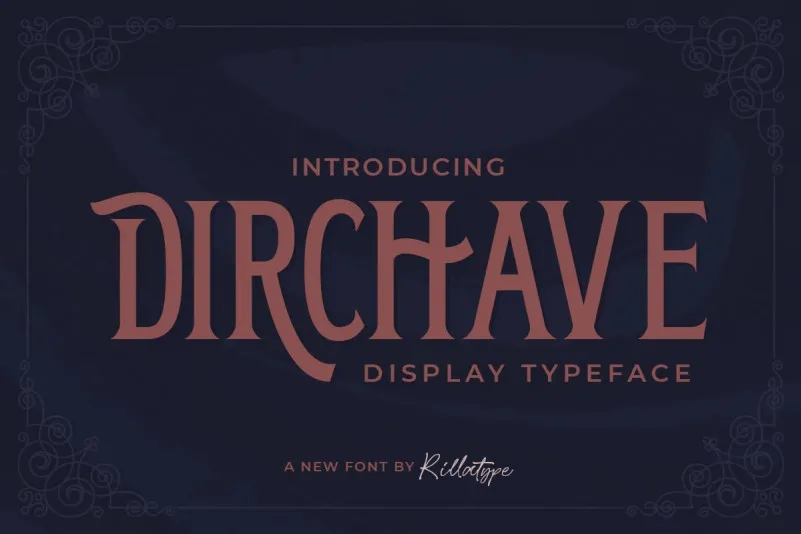
Dirchave Font – Fonte Grátis
Dirchave Font
A fonte Dirchave é uma elegante seleção para designers que buscam um look vintage com muitas alternativas, ornamentações e suporte multilinguístico. Inspirada no estilo clássico dos anos 20 e 30, essa serif font pode ser utilizada em uma variedade de aplicativos, desde embalagens a marcações ou headlines. Seu design moderno mantém o charme do tempo passado, fazendo-o perfeito para ambientes que valorizam um visual arcaico sofisticado. Dirchave é ideal tanto para textos largos e destacados quanto para gráficos de citação e anúncios. Com sua rica variedade de opções, esteve criada pela equipe da Rillatype e compartilhada no site de design 99designs. Se você está buscando uma fonte que não só se destaca por seu visual clássico, mas também oferece um amplo leque de personalizações, Dirchave é o ideal para seus projetos.